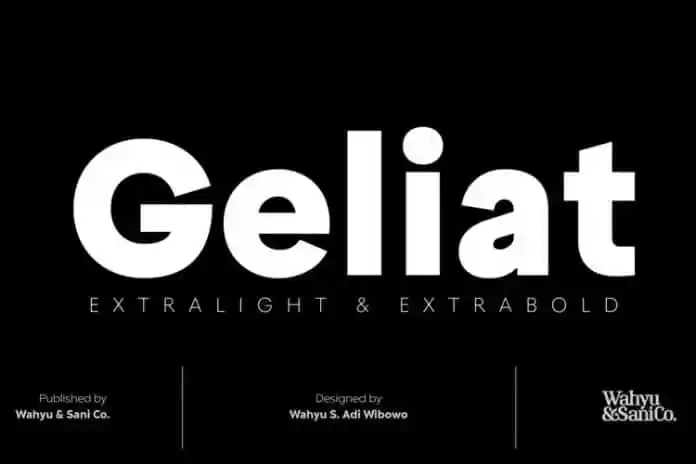
Geliat Sans Serif Font – Download Grátis
A Geliat Sans Serif é uma fonte sobrinho serifa que surgiu no espírito do ritmo regular e das tipografias sans serif geométricas convencionais, que tendem a ser simplesmente acessíveis para leitores. Ela apresenta um caráter forte, bold e robusto, fazendo uso versátil em diversas aplicações. A família de fontes da Geliat tem uma similaridade notável com a Creo, enquanto sua versão alternativa apresenta letra geométrica convencional. Esta fonte foi criada pelo site 99designs e oferece duas opções diferentes, cada uma com um conjunto de caracteres padrão único. As características distintas da Geliat incluem facilidade na leitura por seu design limpo e forte, sua versatilidade em vários usos e a simplicidade de seus elementos gráficos. Seja para rótulos ou designs digitais, a Geliat Sans Serif é uma opção perfeita que combina modernidade com força e robustez.